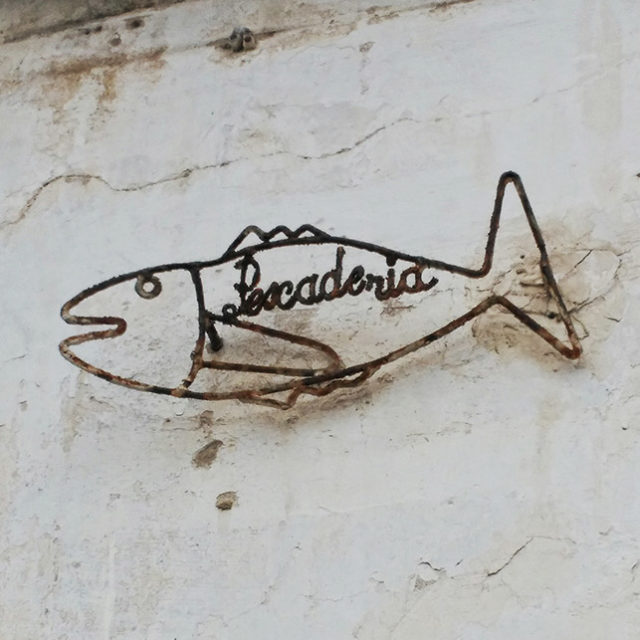
Rótulos y Peces
Francisco Javier Iturri nos ha mandado esta foto de este pequeño rótulo que se ubica en Santa Olalla, cerca Bárcena de Pie de Concha. Un juego tipográfico que la palabra «Besaya» conforma la forma de un Pez.
Esto nos recuerda que en Santander hay un pequeño rótulo de una pescadería, que también juega con la forma del pez como continente de la tipografía.